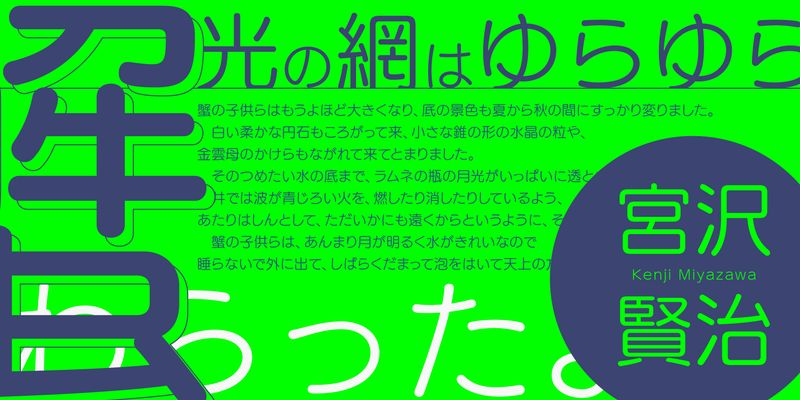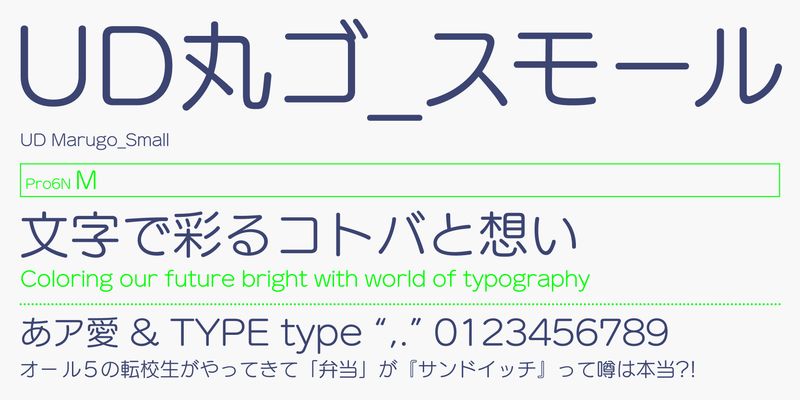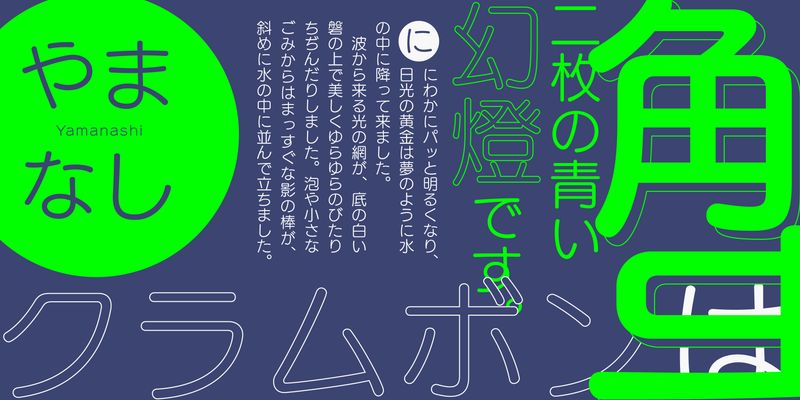
Diese Schrift basiert auf der UDMarugo_Large, wurde aber so umgestaltet, dass sie sich für lange Texte eignet. Um die Lesbarkeit zu verbessern, wurde die Größe der lateinischen und der Zahlen-Glyphen um 2 % reduziert und die Größe der Kana-Glyphen angepasst, so dass diese Glyphen neben den anderen gut ausbalanciert sind und das Schriftbild besser lesbar ist. Diese kleinere Version der UDMarugo-Schriftfamilie eignet sich gut für lange Texte.